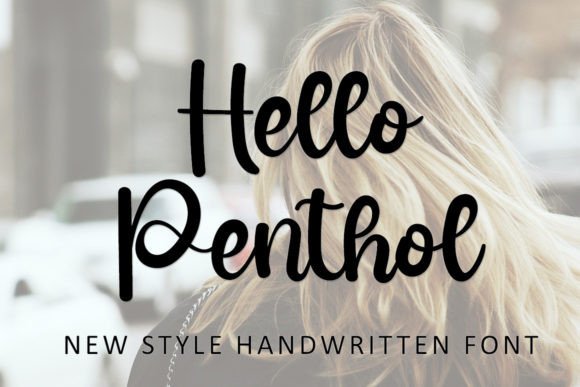
Hello Penthol
قد يكون العثور على عناصر التصميم المناسبة أمرًا صعبًا، ولكن Hello Penthol يقدم مجموعة استثنائية ترتقي بعملك على الفور.
سواء كنت تقوم بإنشاء منتجات الطباعة عند الطلب أو دعوات الزفاف أو رسومات وسائل التواصل الاجتماعي، فإن Hello Penthol هو الخيار المثالي.